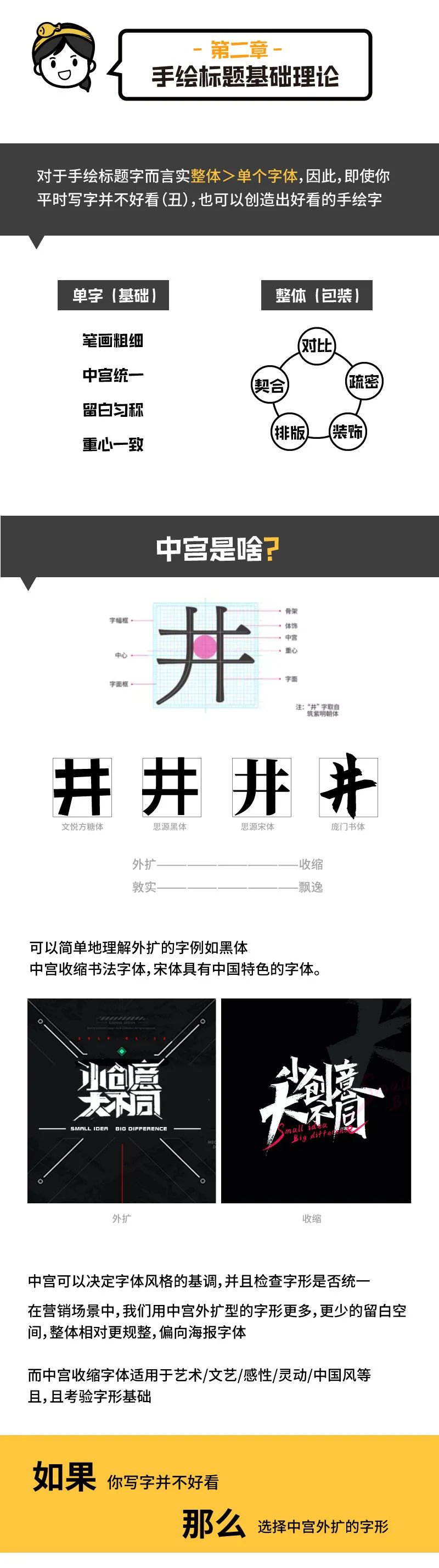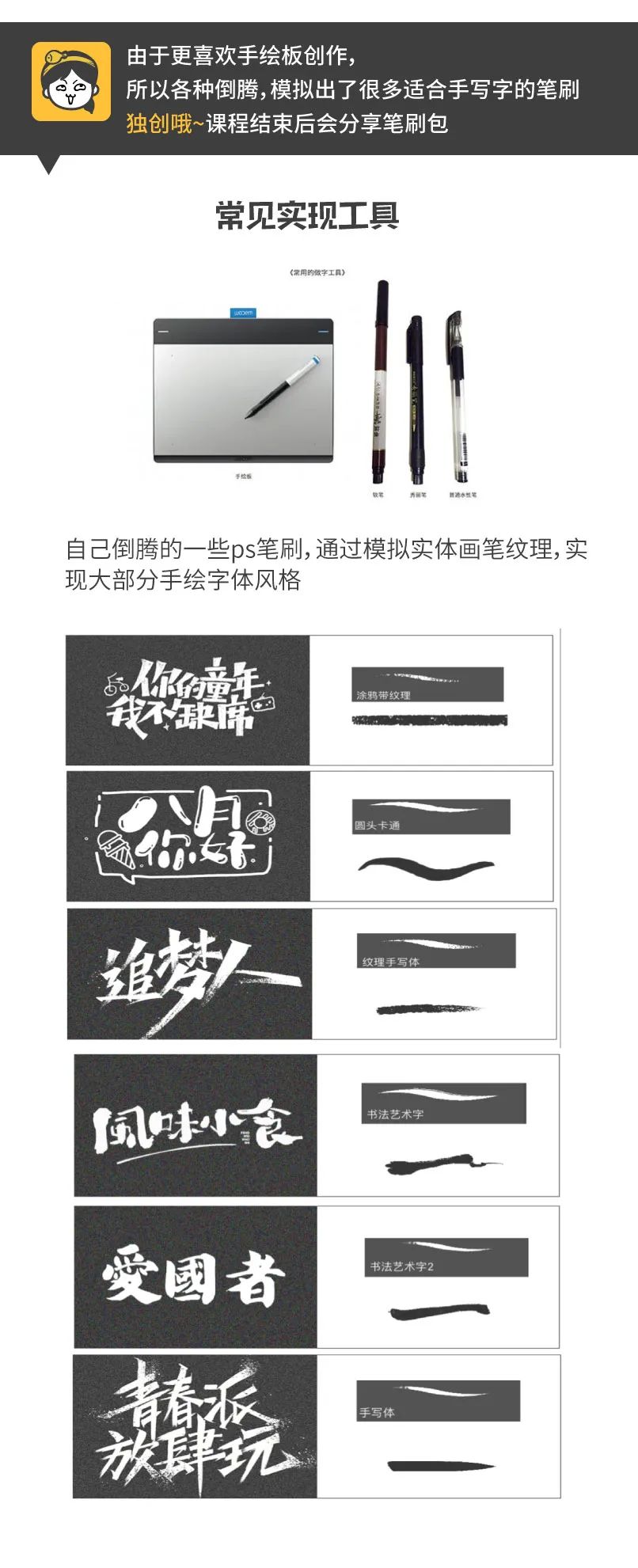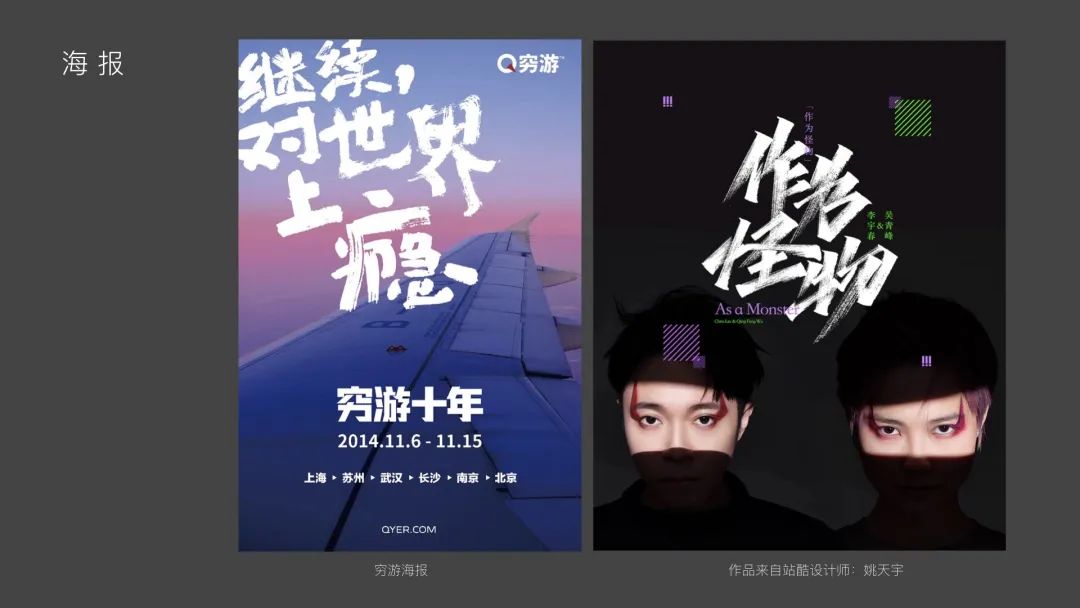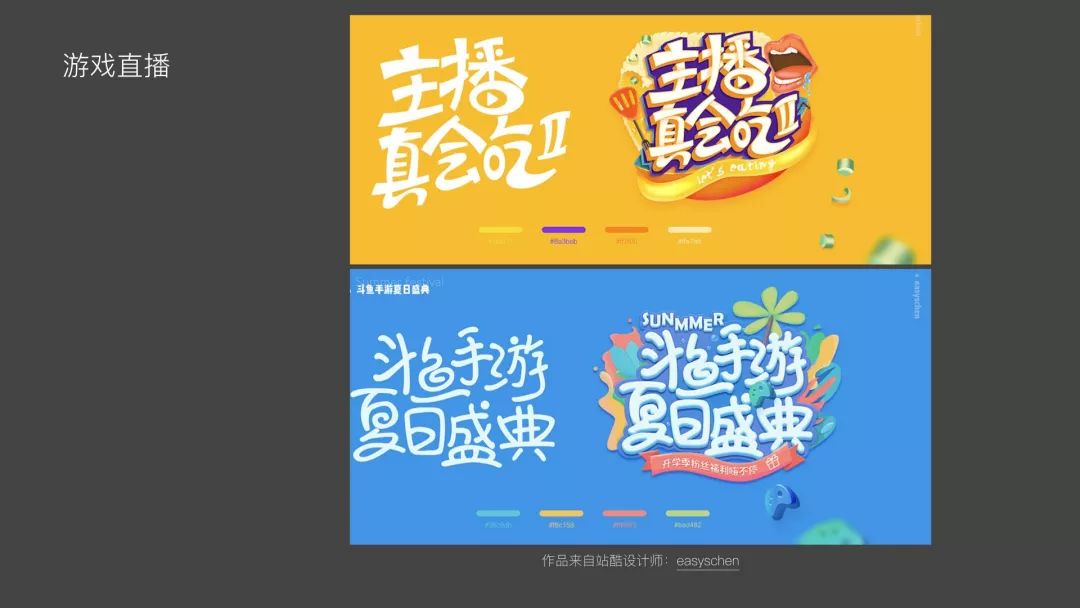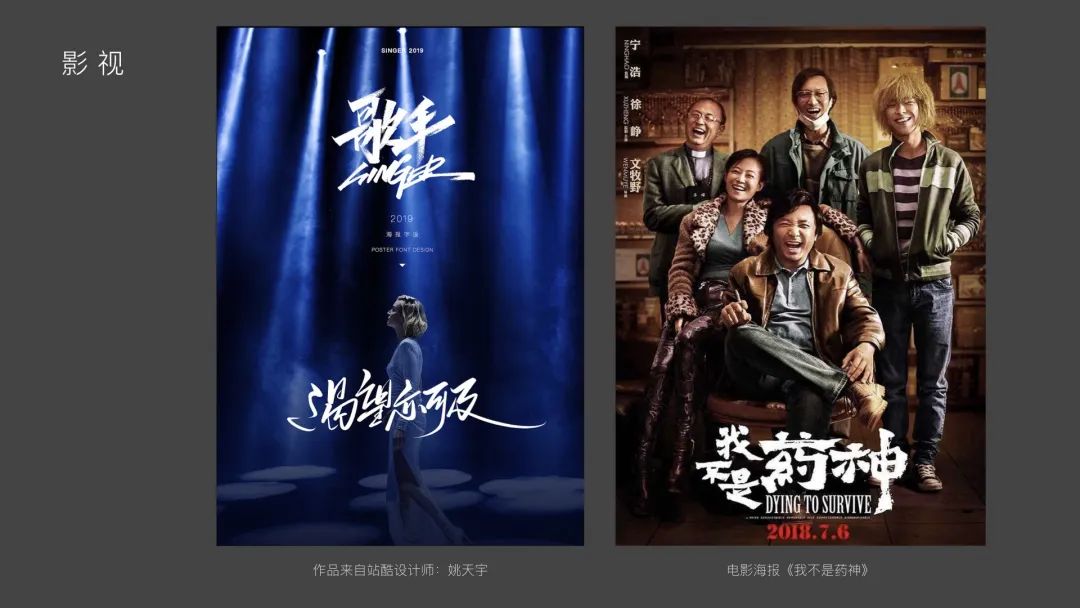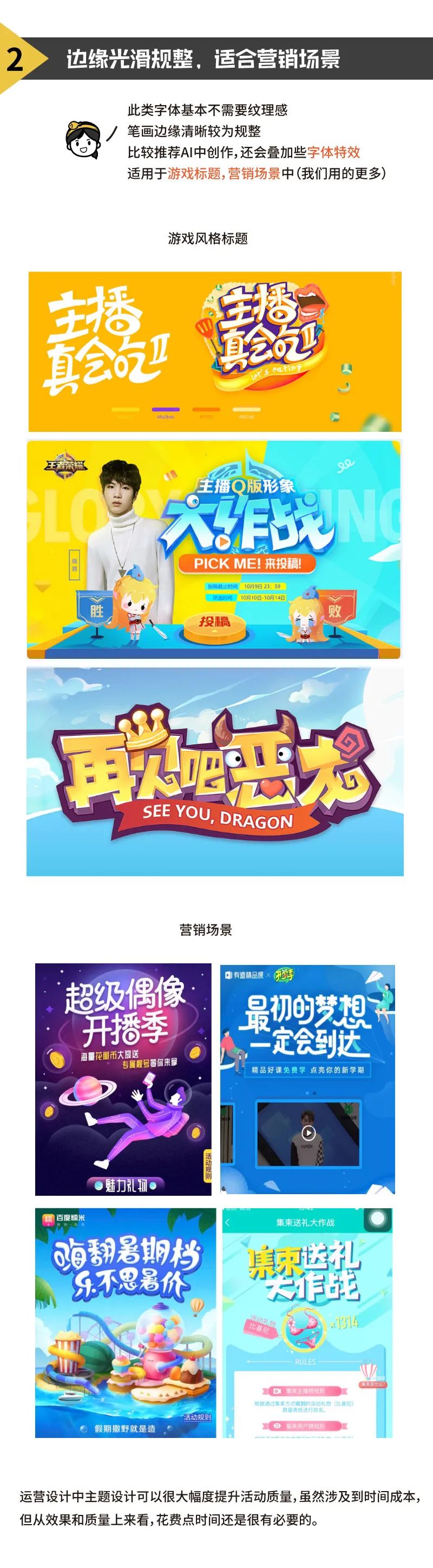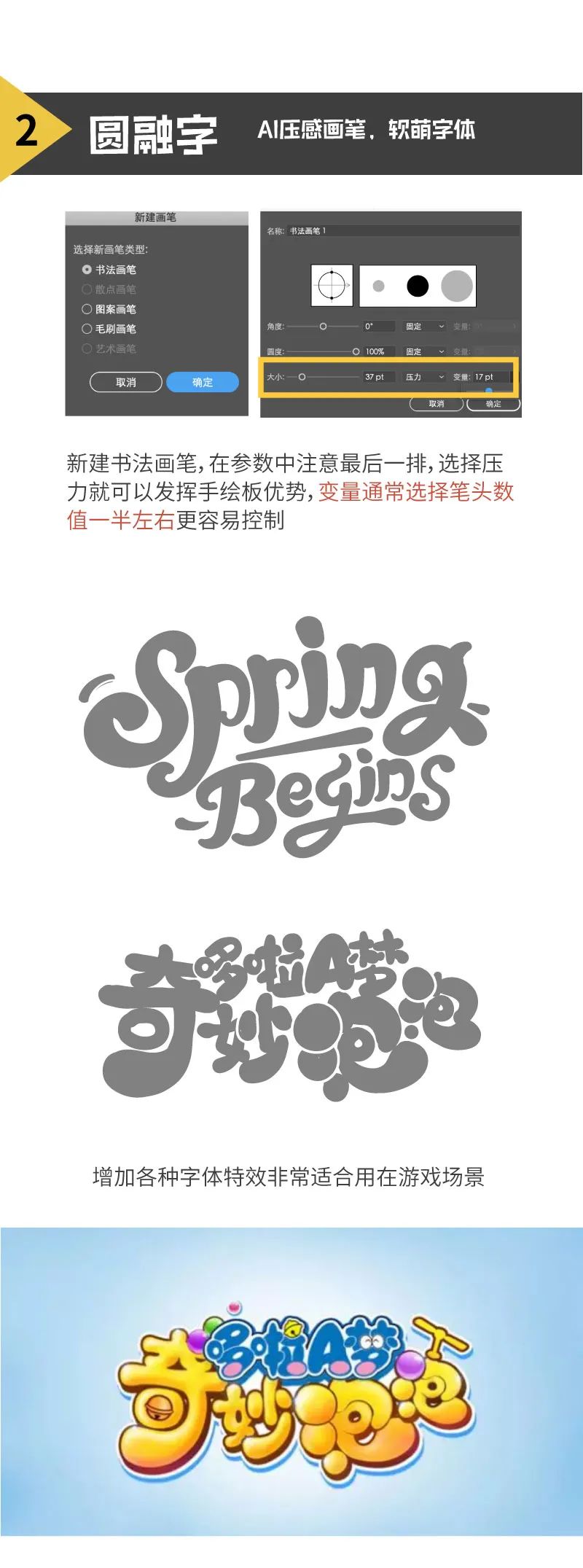
又A又飒的手绘字怎么做?一篇干货就搞定
上周五柚子分享了想让字体更撩人,不妨从歌名设计开始,就有人在后台留言,希望多一些技巧教程。
所以今天满足你,来自站酷的设计师:鱼饼的id,结合案例和实操,教你怎么创作手绘字,看完你一定有所收获(https://www.zcool.com.cn/article/ZMTA0MTYyOA==.html)。